השאלון עם בר מזרחי
הכירו את בר מזרחי, יליד 2000 מגבעתיים, ובוגר טרי של המחלקה לתקשורת חזותית בשנקר. במהלך לימודיו התאהב והתעמק בעיקר בעולמות המיתוג והטיפוגרפיה. בתהליכי העיצוב שלו הוא נהנה במיוחד לצלול לפרטים הקטנים, להישאב למחקרים מעמיקים ולשחק בלי סוף עם אותיות. מחוץ לעולם הגרפי, בר אוהב לשמוע מוזיקה, לטפח את אוסף הספרים והדיסקים שלו, לצפות בטלוויזיה טראשית ולחקור נושאים רנדומליים שמסקרנים אותו באותו רגע.
היי בר, מה שלומך? איפה אנחנו תופסים אותך השבוע?
היי! הכל מעולה, כרגע אני נח קצת אחרי סיום תערוכת הגמר. 😊
מזל טוב! אתה מעדיף לעבוד לבד או בצוות?
גם כשאני עובד לבד, אני עובד בצוות. אני אוהב לשתף את חבריי בתהליכי העבודה שלי ולשמוע מה הם חושבים – זה מעניין לראות איך משהו שהתרגלתי אליו מתקבל בעיניים חדשות. לפעמים זה מאיר לי כיוונים חדשים או עוזר לי לדייק את מה שכבר עשיתי.
על איזה פרויקט מעניין עבדת לאחרונה?
במהלך שנה ב׳ עלתה לי שאלה שסקרנה אותי – ״איך הייתה נראית בובת אופנה ישראלית?״. עם הזמן, הבנתי שזו השאלה שבה רציתי להתמקד בפרויקט הגמר שלי, וכך נולדה ״רותי״ – סדרת בובות אופנה שכל אחת מהן מייצגת נקודת ציון חברתית ותרבותית בחיים בישראל. בתחילת המחקר שמתי לב שרוב בובות האופנה בעולם עוסקות במוטיבים של הגשמה עצמית ושל פנטזיה, וזה גרם לי דווקא להעביר את הדיסוננס שבין זה לבין החיים בארץ – את המתח והחיכוך שבין אידיאל למציאות. לכן נתתי לכל בובה תפקיד מוגדר וסיטואציה של פעולה או עשייה, הבאים לידי ביטוי גם בשמות הבובות וגם בשפה החזותית, המשלבת בין אסתטיקה של צעצועים לבין דימויים מהאתוס הציוני. השפה האיורית התגבשה מתוך שילוב בין עיצוב ישראלי משנות ה־40-50 (בעיקר בהשראת האחים שמיר), לבין איור של בובות אופנה משנות ה־80-90.
מה הדבר הכי טוב שקרה לך השנה?
השנה השתתפתי בשני ספרים שונים, ויציאתם הייתה די צמודה אחד לשני – ההגדה השנתית של אסופה, בה עיצבתי כפולה לשיר ״והיא שעמדה״, וספר ״תזוזות״ של הוצאת מינוס, אשר מתעד גופנים שיצאו בשנתיים האחרונות (2023–2025), ובו נכלל הגופן ״משאלה״ שעיצבתי במסגרת קורס פונט בשנקר בהנחייתו של אברהם קורנפלד. התרגשתי לראות את העבודות שלי מוצגות בספרים האלו, ואני מקווה להשתתף בעוד ספרים בעתיד.
מה גורם לך להתרגש ולרצות לעצב וליצור?
הפריווילגיה שהיא לעצב בשפה העברית.
מה אתה עושה כשאין לך מוזה?
הלוואי שהייתה לי תשובה חד־משמעית לכך. במקרים כאלה אני משתדל להתרחק מהמסך, לצאת מהבית, לדבר ולבלות עם משפחה וחברים, או פשוט לעשות משהו אחר. לפעמים זה מה שעוזר לי לחזור לעבודה עם ראש נקי ופרספקטיבה חדשה.
מה אתה עושה בשביל הכיף?
אני אוהב להאזין למוזיקה, לראות ריאליטי זול, לאסוף אלבומי מוזיקה, ספרי עיצוב וסרטים, להיפגש עם חברים – וכמובן גם לעצב. 🙃
twig הוא פרויקט שיצר בר מזרחי יחד עם חברותיו אורי עדן והיאא קעואר בסמסטר שלפני פרויקטי הגמר. מדובר בצעצוע שמבקש לחבר ילדים אל הטבע דרך משחק חופשי. הערכה כוללת שני סטים של חמש צורות גיאומטריות פשוטות, עשויות עץ בירץ ו־PVC, שמייצרות חיבור בין טבעי לתעשייתי – ממש כפי שקורה בטבע העירוני. המשחק מזמין ילדים לצאת החוצה, לאסוף ענפים ולבנות אינסוף מבנים בדרך אישית וללא חוקים. מעבר לכך, גובשה גם שפה חזותית שמושפעת מעיצוב צעצועי ילדים משנות ה־60 וה־70, תקופה שקדמה להשתלטות המוחלטת של הטכנולוגיה על חיי היומיום. כפי שמתאר בר: ״הרצון שלנו היה לחבר ילדים לטבע דרך משחק חופשי״. הפרויקט נעשה בשנה ד׳ במסגרת קורס ״עיצוב משנה מקום״, בהנחיית דפנה בלוך ויואב גתי.
יש לך הרגל מגונה?
לנסות כל הזמן להכניס ורוד לפרויקטים...
יצא לך לטייל בחו״ל?
כן, אני אוהב לטייל בעיקר באירופה. בשנה שעברה ביקרתי במוזיאון העיצוב של ברצלונה, שהיה יפהפה ומעורר השראה.
מה משך אותך לתחום?
עטיפות של אלבומי מוזיקה. בתיכון התחלתי לאסוף דיסקים (ממליץ, יותר כיף מתקליטים), והיו כמה אלבומים ומוזיקאים שהתחלתי להקשיב להם רק מפני שנחשפתי אליהם בחנויות מוזיקה, והעטיפות שלהם סיקרנו אותי. עד היום הפורמט הזה מקסים בעיניי – בחוברת קטנה בגודל 12×12 ס״מ יכולים להופיע דימויים מגוונים לגמרי – מילים, תמונות ושלל ויזואליות מעניינות.
לאן ניסית להתקבל ללימודים ולאן התקבלת?
ניסיתי להתקבל לשנקר ולבצלאל, ולשמחתי התקבלתי לשנקר.
איזה מרצה השפיע/ה עליך במיוחד?
יעל בודשר. היא ממש פתחה בפני את עולם המיתוג. דרך ההנחיה שלה, וגם דרך העבודות של הסטודיו שלה, הבנתי כמה מיתוג יכול להיות מהלך רוחבי, חכם, אסתטי ומדויק.
איזה מעצב/ת השפיע/ה עליך יותר מכל?
אני חושב שאני בעיקר מושפע מעיצוב ישראלי ופחות ממעצב ספציפי. אני נהנה מהשפה המקומית שנבנית פה בארץ. ובכל זאת, בשנתיים האחרונות אשר קלדרון הפך לדמות השראה משמעותית עבורי – יש משהו בצבעים הנועזים, בלטרינג המקורי ובאופטימיות שנוכחת בהרבה מהעבודות שלו שפשוט מלהיב אותי. זה עושה לי חשק ליצור ולנסות לאמץ חלק מהעולם שהוא יצר לתוך השפה העיצובית שלי.
במה היית עוסק אם לא היית מעצב?
כוכב פופ או ספר.
ספר פרוזה/עיון אחרון שקראת.
המדריך לחיים של מיס פיגי מאת הנרי בירד.
רוצה להמליץ על ספר עיצוב?
More is More: Designing Bigger, Bolder, Brighter של הוצאת Victionary. מעבר לכריכה המשגעת, הספר מלא בהשראות מגניבות ומגוונות למיתוג מקסימליסטי, מוגזם ונועז. הוא ההפך הגמור ממינימליזם, וזה בדיוק מה שהופך אותו לכל כך כיפי בעיניי.
אתר השראה מדליק שאנחנו לא מכירים.
מרכז שנקר לתיעוד וחקר העיצוב בישראל. מעבר לאתר הוא גם מקום פיזי עם שלל תכנים ארכיוניים מדהימים (ממליץ לבקר!). האתר מצוין למציאת השראות מקומיות, וגם ללמידה על תרבות העיצוב בארץ. לשמחתי יצא לי גם לעבוד כמה פעמים עם המרכז ואף לעשות בו התמחות קיץ, במסגרתה תיעדתי את עבודותיה של המאיירת דנה שמיר ואף ערכתי ראיון איתה.
באיזה פונט אתה רוצה שיכתבו על המצבה שלך?
יצא לי לעצב גרסה עברית לפונט שלנה דל־ריי השתמשה בו לאלבום Born To Die, אז להשתמש בו יהיה מאוד משעשע וסמלי, בנוסף לכך שאהבתי את איך שהשם שלי נראה כתוב בו. נראה לי שאתחיל לתכנן את המצבה שלי אחרי הריאיון הזה... 🤔
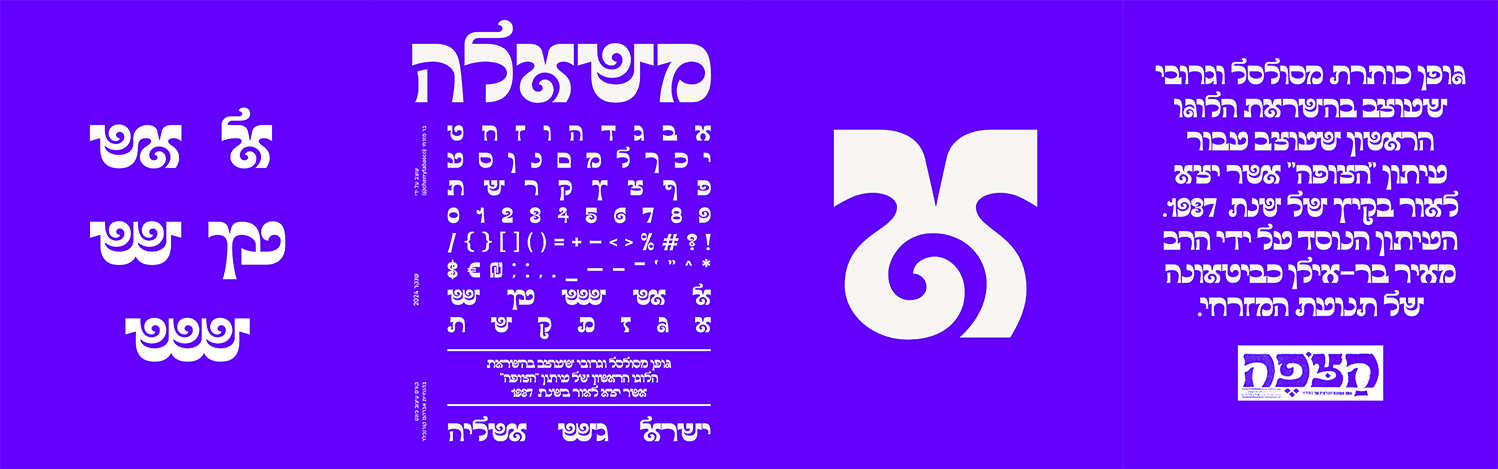
"משאלה" הוא גופן כותרת מסולסל וגרובי שעוצב על־ידי בר מזרחי במסגרת קורס עיצוב פונט בשנקר בהנחיית אברהם קורנפלד. מקור ההשראה הגיע מהלוגו הראשון של עיתון ״הצופה״, שנוסד בשנת 1937 על ידי הרב מאיר בר־אילן כביטאונה של תנועת המזרחי. במהלך פיתוח הפונט, בר הבין שיהיה נכון לתת לחלק מהאותיות שתי גרסאות – אחת בסיסית ואחת מסולסלת – מה שהעשיר את השפה הטיפוגרפית של הגופן. לדבריו: ״זה הגופן ה׳אמיתי׳ הראשון שעיצבתי, ולגמרי השאיר לי טעם לעוד״.
יש לך המלצה מוזיקלית?
גיליתי את שושנה היזמי לגמרי במקרה, כשנהגתי בלילה אחד והרדיו היה פתוח. המוזיקה שלה מאוד שונה מהדברים להם אני מאזין בדרך כלל, אבל השירים שלה מיוחדים – במיוחד ההפקה והכתיבה. בזמן המלחמה השירים שלה קיבלו עבורי משמעות חדשה, למרות שהם נוצרו קודם.
מהי משמעות החיים?
היא נעה בין ״נסיכת פופ״ של רוני דואני לבין ״לשמוח ולרקוד״ של האחיות יוספי.
מה שם החיבה שלך?
ברצ׳וק/ברוש במשפחה, ברמיז בשכונה, ברבי בשנקר.
קיצור מקלדת אהוב
cmd+shift+4 (צילום מסך במק).